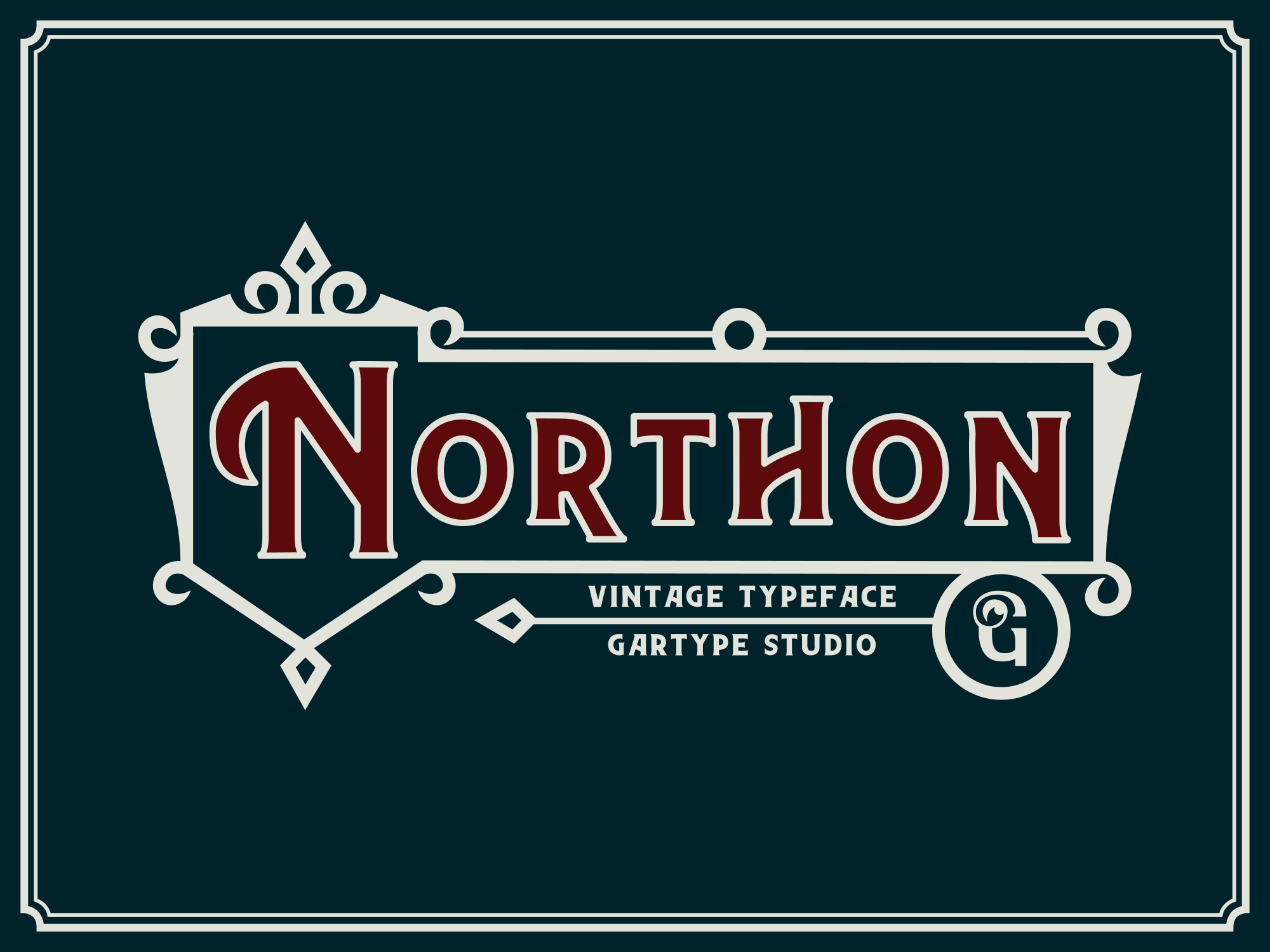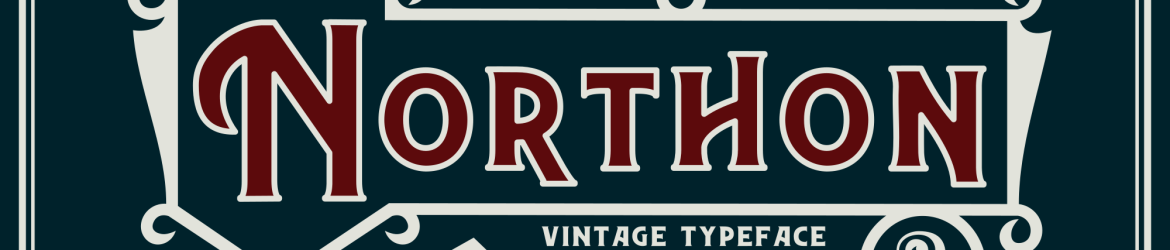
Northon Font and Ornament – Download Grátis
Olá, designers! Hoje vamos apresentar a vocês Northon, uma fonte vintage criada pela Gartype Studio. Northon vem em dois formatos: Northon e Northon Outline. Além de serem versáteis para seu projeto, oferecem também um conjunto de ornamentos que ajudará a dar vida ao seu trabalho final!
Designer: Gartype Studio